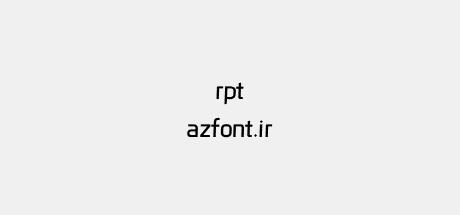
rpt
فونت زیبای رایگان rpt
قلم زیبای rpt-Regular از سری قلم های بسیار زیبا برای تایپوگرافی و لوگو تایپ می باشد.این قلم در وزن Regular و توسط Tarek Atrissi طراحی و منتشر شده است.